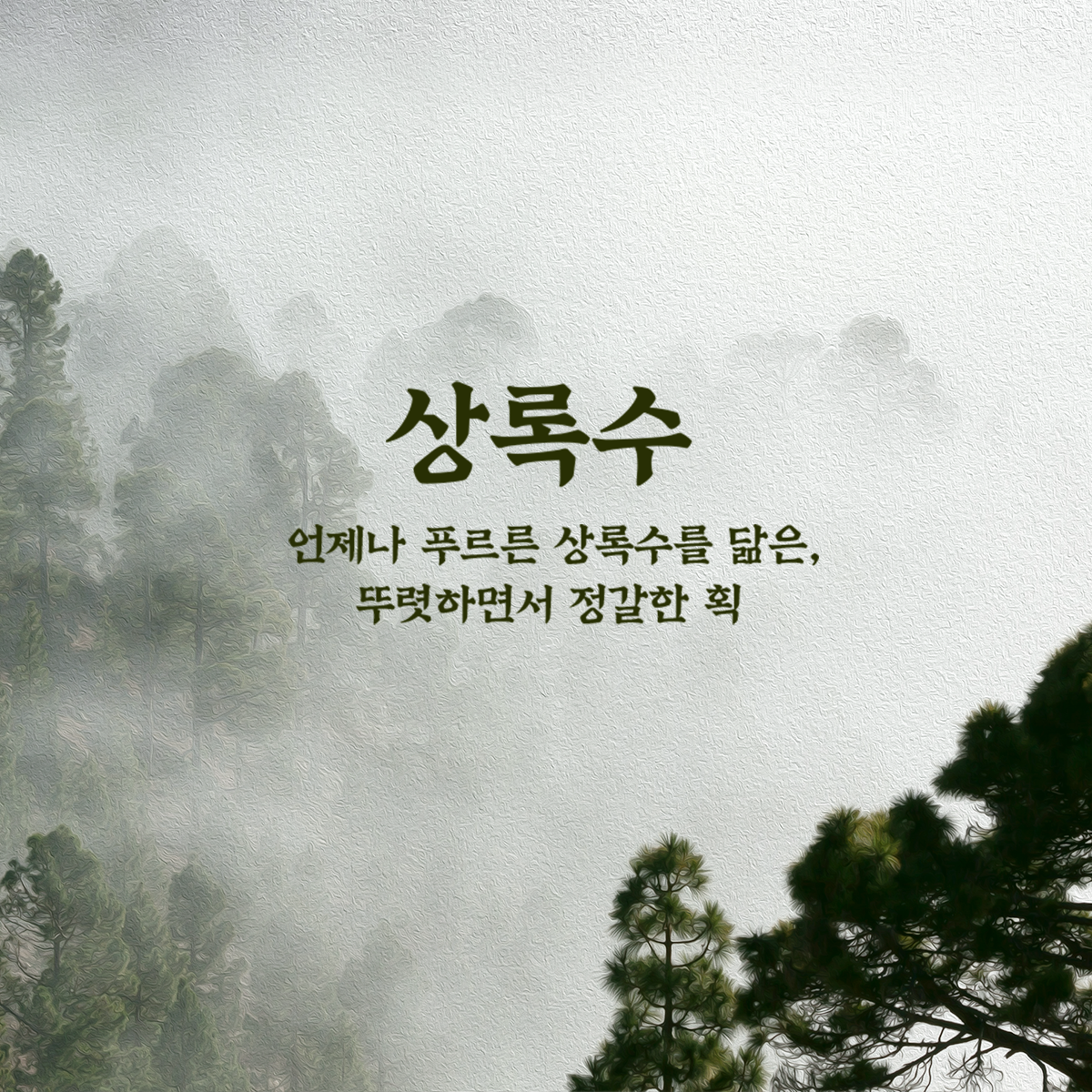
- 산돌 상록수는 힘있는 획을 통해 절제된 아름다움을 느낄 수 있는 폰트이다.
단아하고 바른 여사서 폰트를 모티브로 삼아 재해석 하였으며, 뚜렷하면서도 정갈한 획이 특징으로 붓을 세게 눌러쓴 듯 힘이 느껴지는 획의 시작과 마무리를 통해 강하고도 절제된 아름다움을 표현했다.